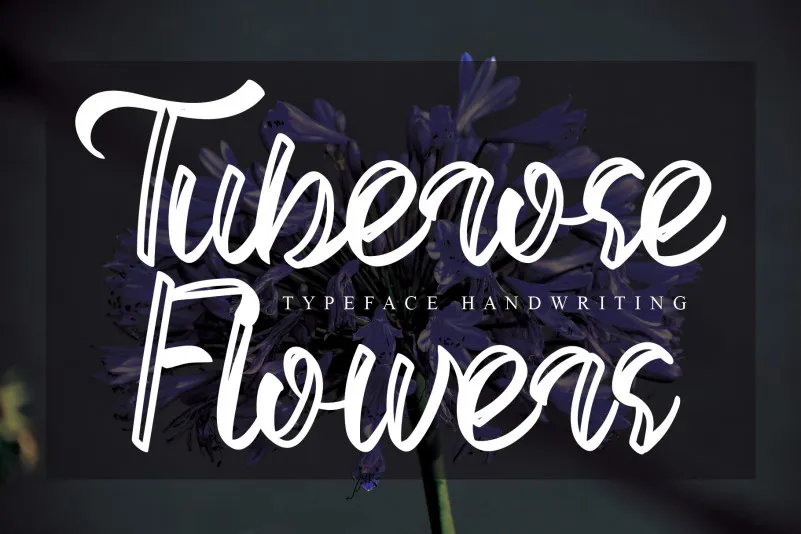
Tuberose Flowers Script Font – Download Grátis
Tuberose Flowers Script Font é uma elegante fonte escrita a mão que traz delicadeza e sofisticação ao seu projeto. Ela apresenta letras distintas e redondas, criando um toque único que torna essa fonte verdadeira arte. Seus traços finos e detalhes perfeitos são ideais para criar designs surpreendentes. Uma vez que esse é o tipo de fonte perfeito para qualquer design que deseje dar vida a uma atmosfera romântica ou elegante, pode ser usada em cartões de aniversário, gráficos promocionais e até mesmo em artigos de floricultura. Recomendamos este tipo de fonte para quem busca dar um toque especial ao seu trabalho, seja por sua simplicidade impressionante ou pela profundidade que suas letras entregam.